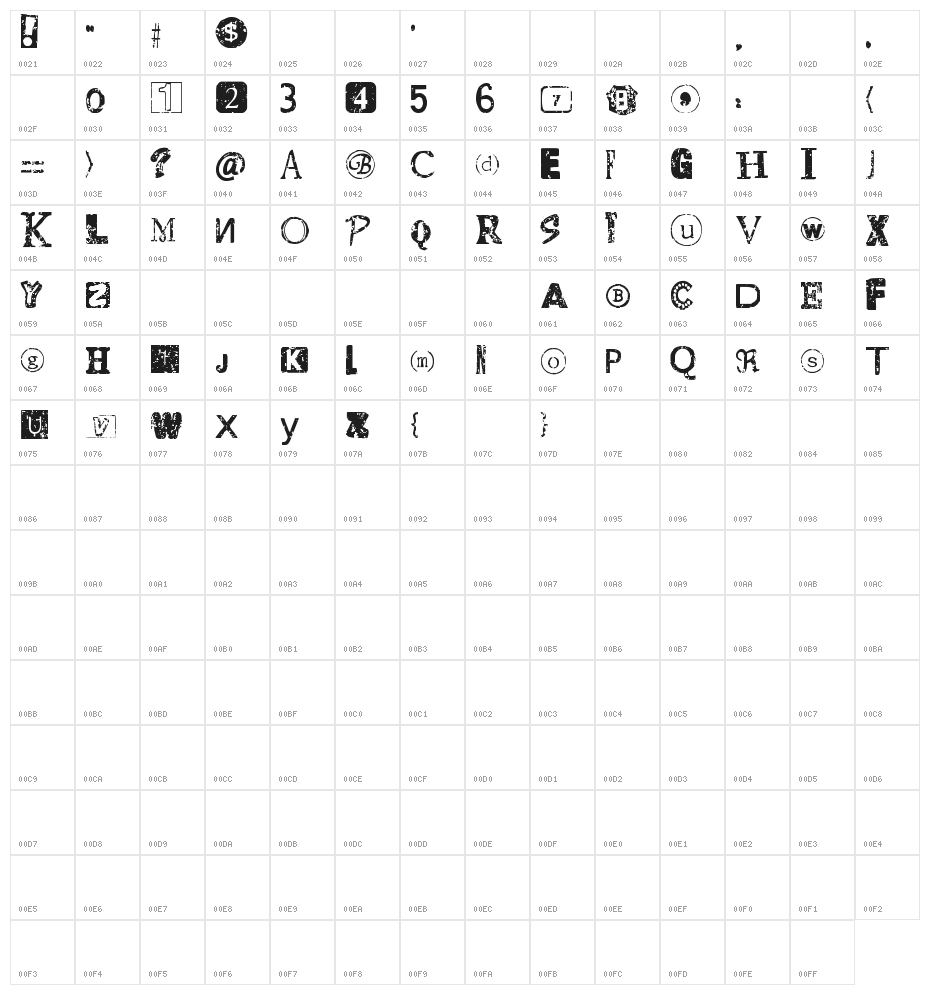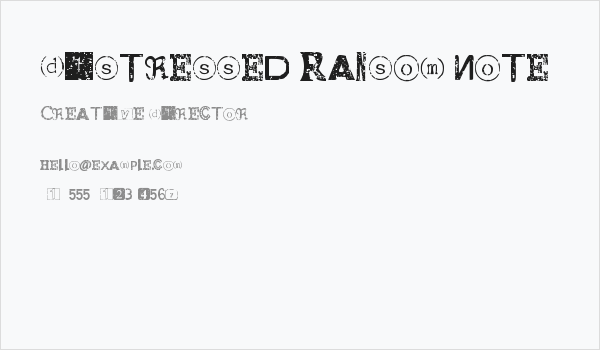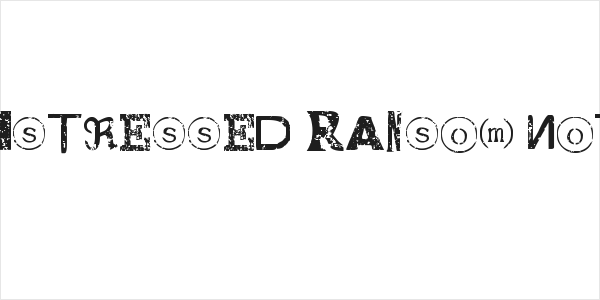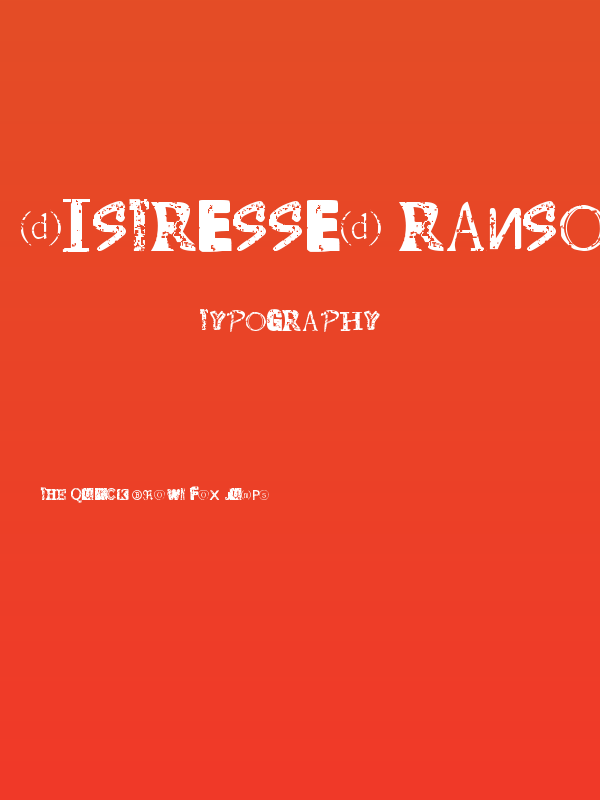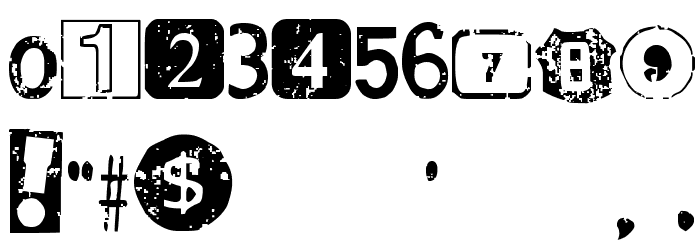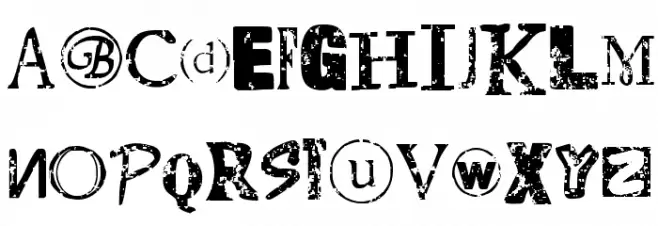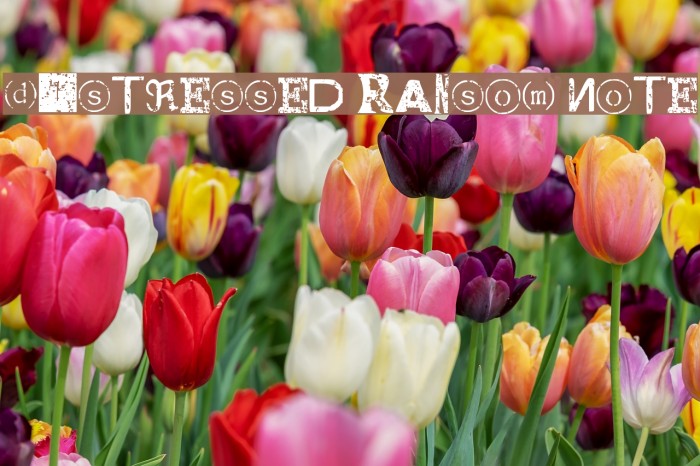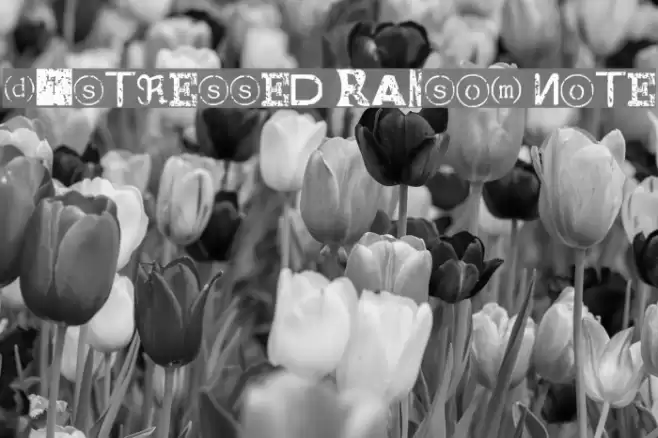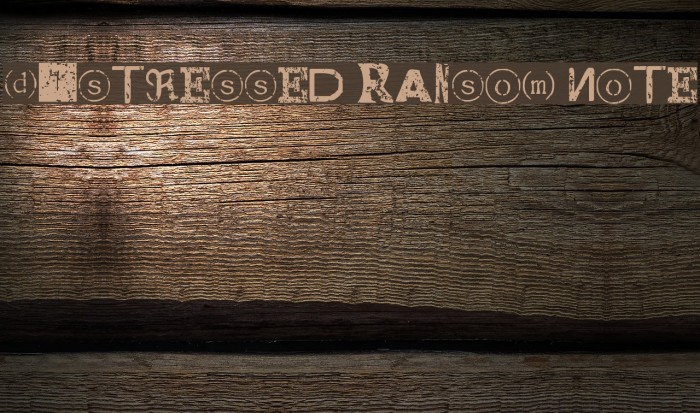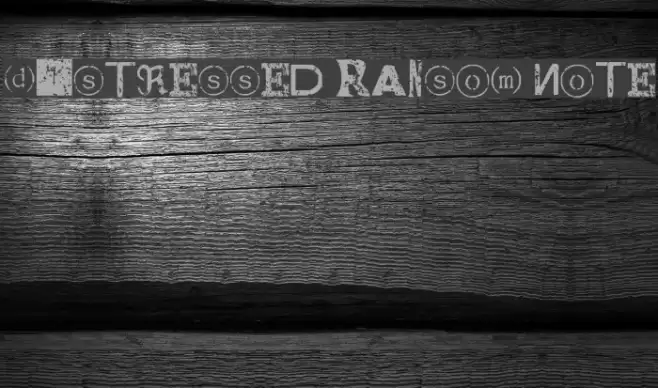
Distressed Ransom Note Font
| 全体的なスタイル | Vintage, Distressed |
| 用途 | Headlines, Artistic projects, Posters |
| おすすめプロジェクト | Ideal for mystery-themed posters, retro designs, artistic projects, and any creative work that benefits from a distressed, handmade look. |